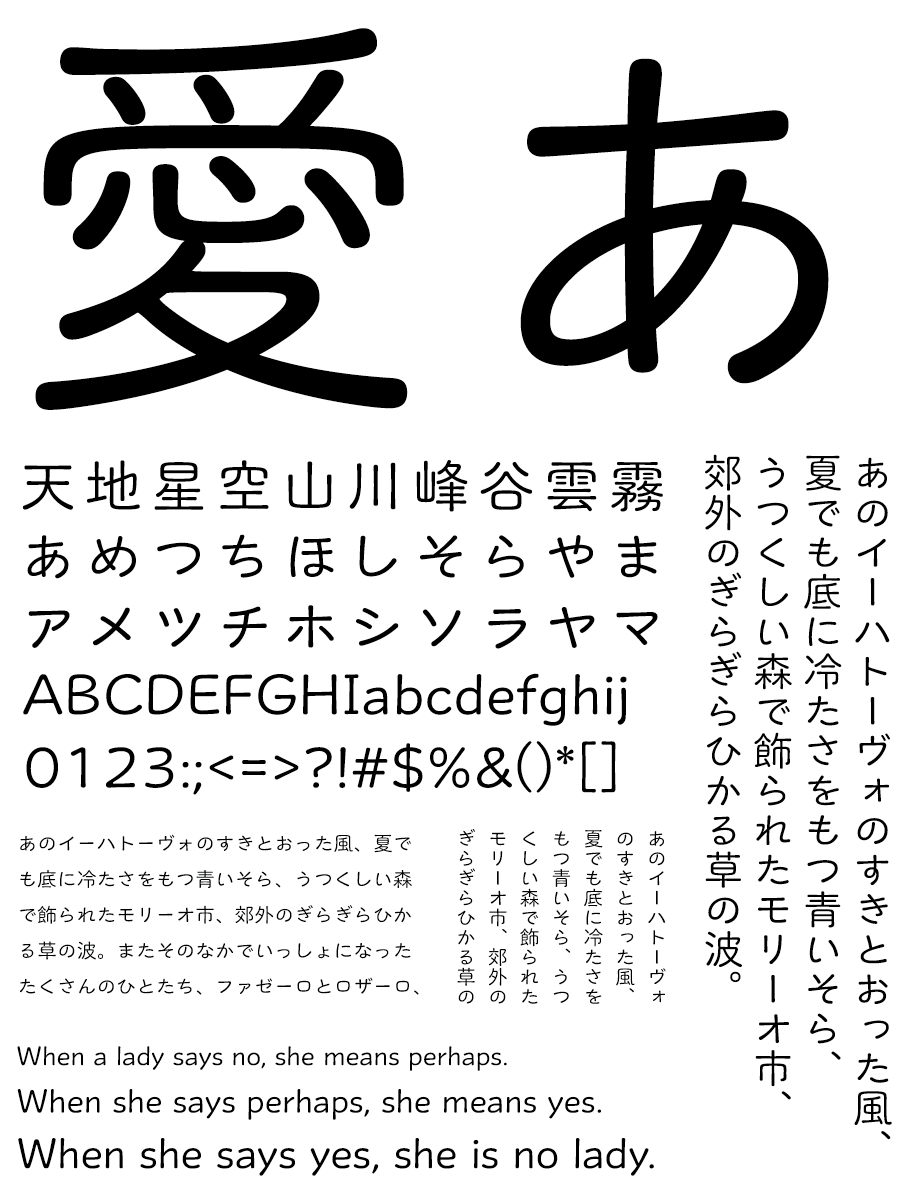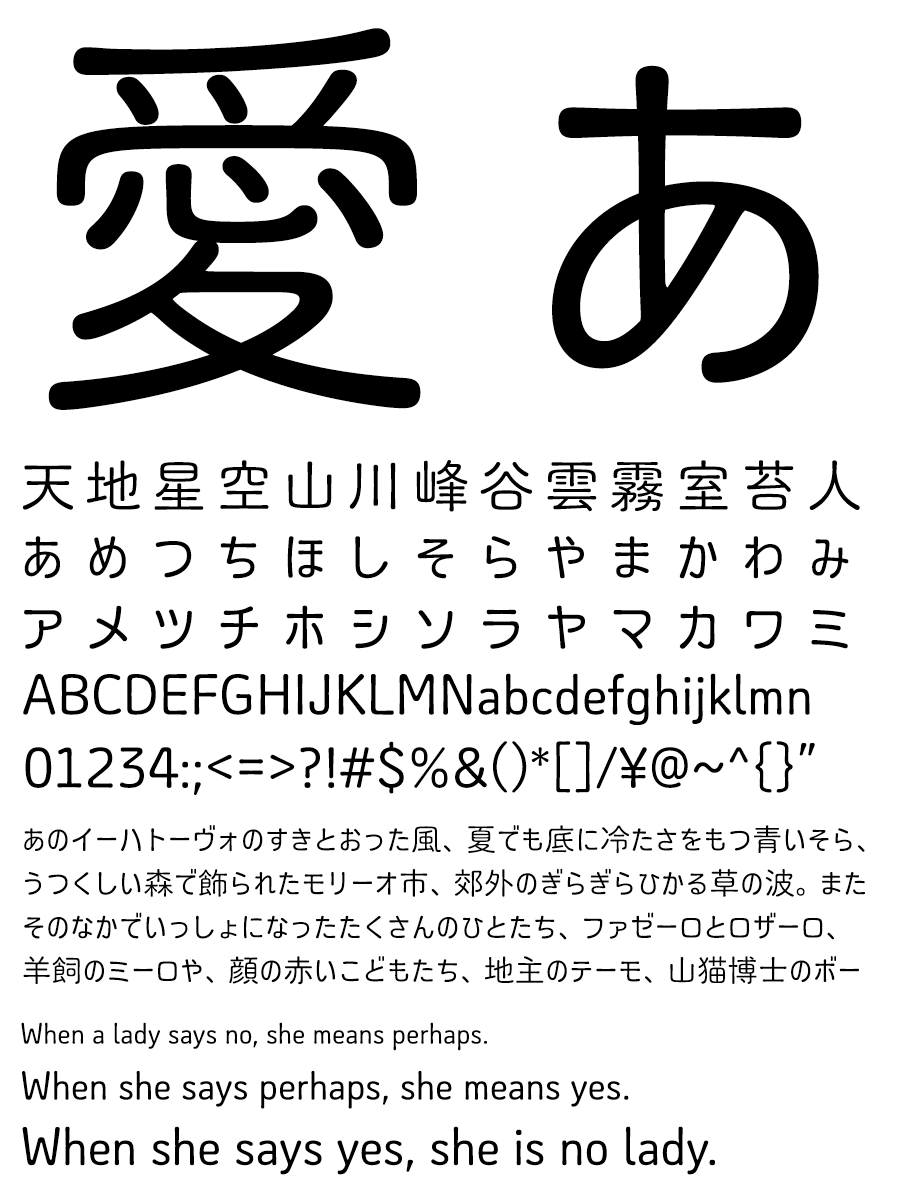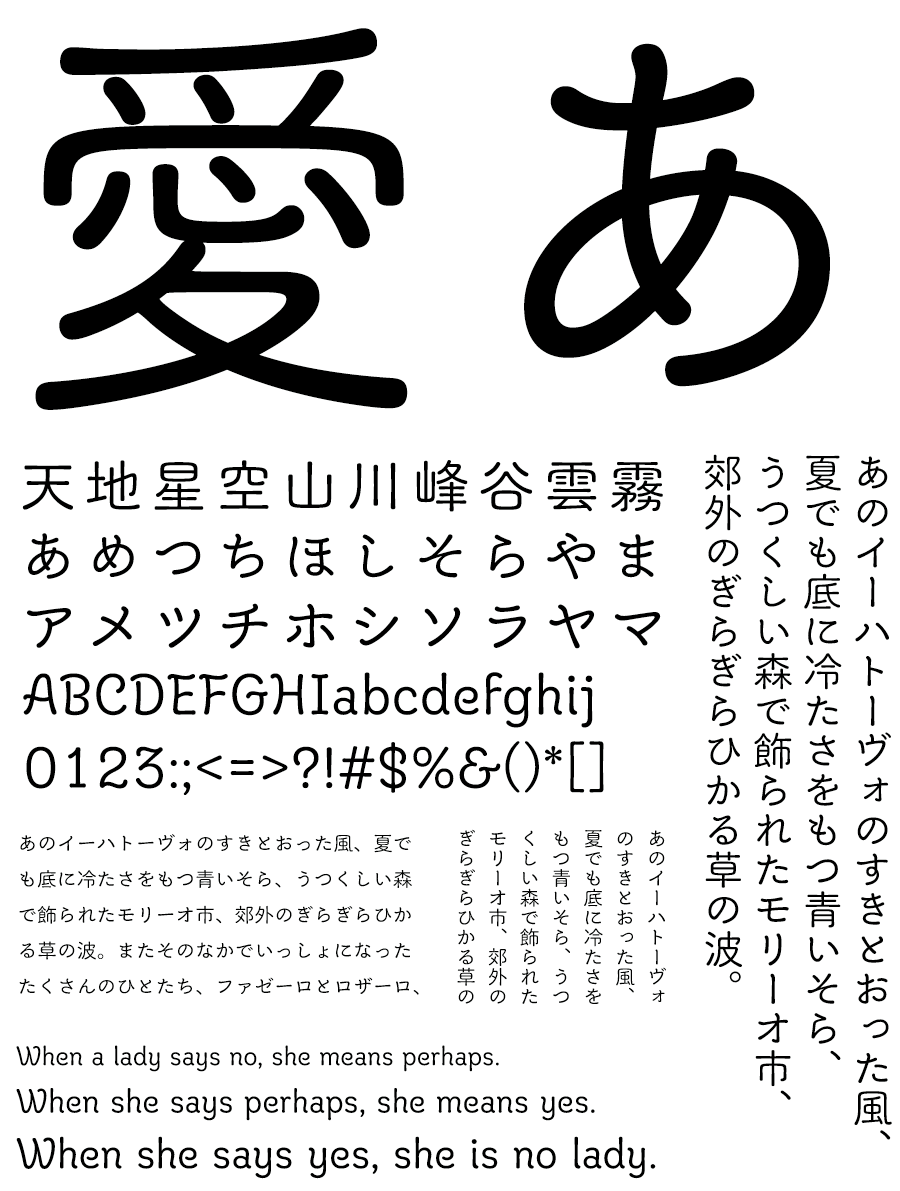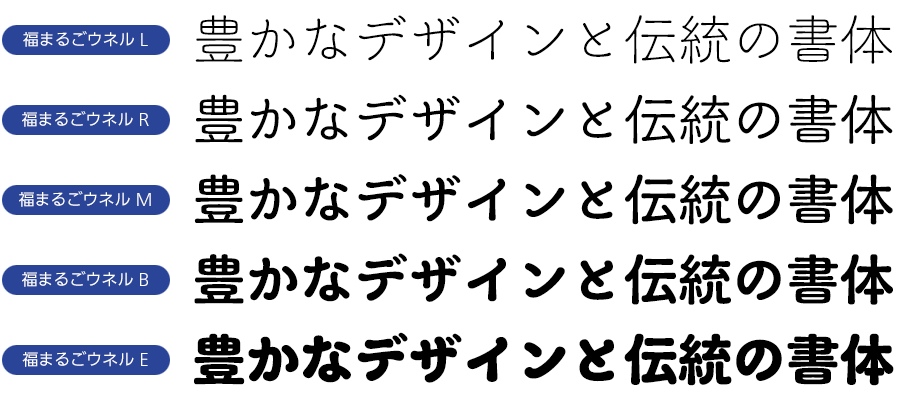
イワタ 福まるごファミリー
人気書体「イワタ福まるご」ファミリーに、5つのバリエーションが追加
有機的な曲線で構成された、これまでにないオールドスタイルの丸ゴシック体「イワタ福まるご」。2020年3月発売以来の人気書体に、「アソブ」「ウネル」「カタル」「タタズム」「キザム」の5つのバリエーションが加わりました。
ファミリーの特徴
イワタ福まるご
見出しから長文組版まで広く使いやすいよう仮名はオーソドックスで読みやすい骨格に、欧文は有機的なフォルムでまとめています。
イワタ福まるごアソブ
カジュアルさの中に軽快なリズムを持たせた書体で、親しみやすい遊び心に、ノスタルジックな面持ちも備えています。その姿は原っぱで楽しく遊んだ少年時代を連想させます。
イワタ福まるごウネル
右上がりで華やかな書体です。装飾的な曲線を多く用いた芸術「アール・ヌーヴォー」から着想を得たデザインで、その様式は浮世絵からも影響を受けていると言われます。うねるような筆遣いは北斎の大波を想起させます。
イワタ福まるごカタル
映画字幕などで使われていた特徴的な文字をモチーフにした書体です。線画が長く高低差の少ない骨格と、線端の抑揚が手書きのイメージを伝えます。レトロな映写機で映し出された名作が優しくゆっくりと語りかけるかのようです。
イワタ福まるごタタズム
金属活字の古いゴシック体の骨格と幅広な欧文を合わせた書体です。味のあるアンバランスさや小さな拗促音など活字時代に培われたテイストを色濃く取り入れています。時代を超えても色あせない重厚な佇まいは、夕日に染まった富士山を彷彿とさせます。
イワタ福まるごキザム
水平垂直に構成された長体かなを、横方向のラインに沿って揃えた機械彫刻のような書体です。タイプライターで規則正しく打たれたような律儀さに柔らかい曲線が合わさり、整然としていながら堅苦しくない印象を刻みます。
イワタ福まるご
イワタ福まるごアソブ
イワタ福まるごウネル
イワタ福まるごカタル
イワタ福まるごタタズム
イワタ福まるごキザム
使用フォント: 福まるごタタズム 福まるごキザム
使用フォント: 福まるごアソブ 福まるごタタズム
使用フォント: 福まるごウネル 福まるごカタル
イワタ福まるご L/R/M/B/E
有機的な曲線で構成された、これまでにないシルエットの丸ゴシック体。「もっちりぽってり」。見出しから、しっかり文字組までこなせます。